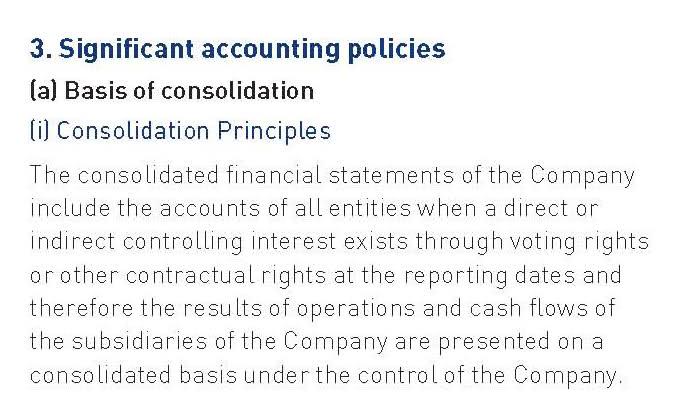
Helft ihr alten Hasen mir?
Wo ist das her? Welche Firma betrifft der Text? Warum ist der nicht anti-aliased?
entschuldigt die schlechte Darstellung , ich hab aus einem schlechten jpeg einen schlechten Ausschnitt genommen und diesen noch vergrössert . :? Antialiasing und rendering lass ich mir gern von Euch erklären :D
Antialiasing verlegt :hammer: einen weichen Teppichläufer auf die harte Pixeltreppe und das Rendering bringt dir diese Rechenschieberei auf den Bildschirm. :schonklar:
Ausführlicher:
Speziell für Schrift ist diese Grafik interessant:
Oben bzw. links: Ohne antialiasing --> mit sichtbarem Treppeneffekt
unten bzw. rechts: Mit Antialiasing --> Die Treppen werden durch Graue Pixel ausgeglichen, die Schrift wirkt trotz dem grobem Bildschirm-Pixelraster glatter.
Es gibt aber verschiedene Methoden, die Kanten zu glätten – Details in Norberts Link.